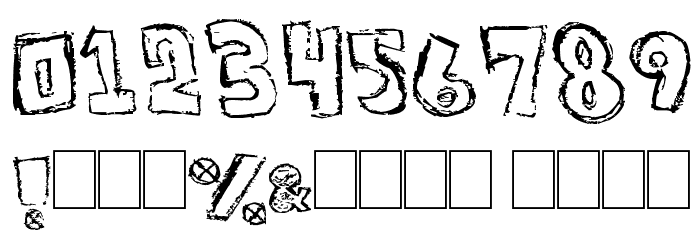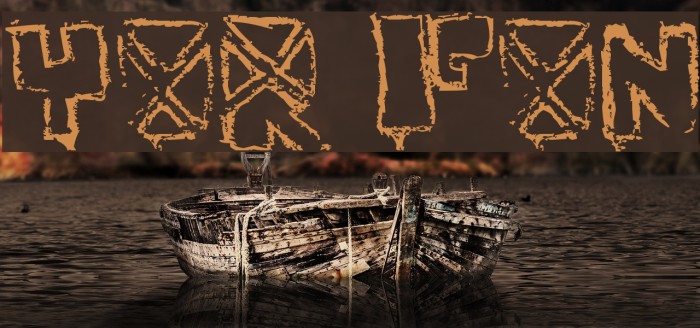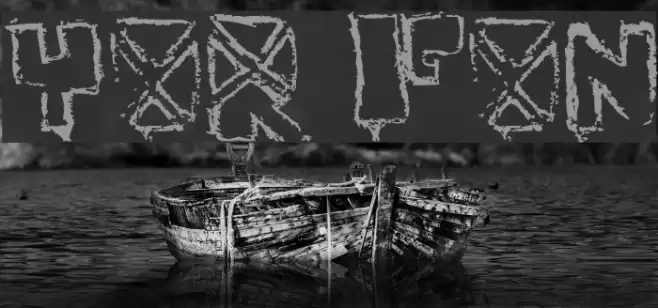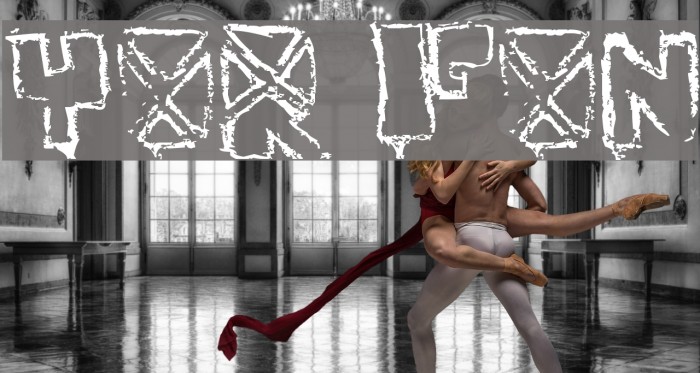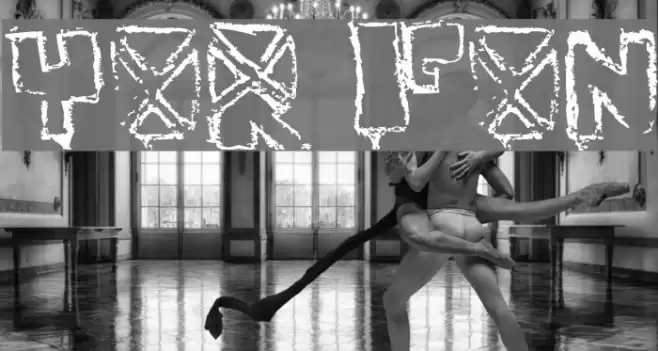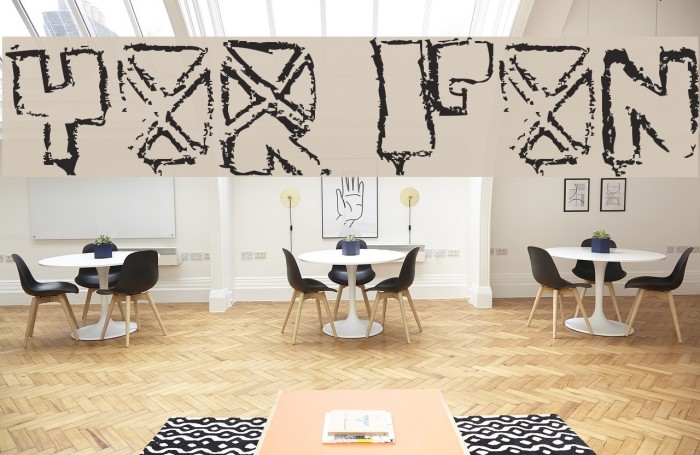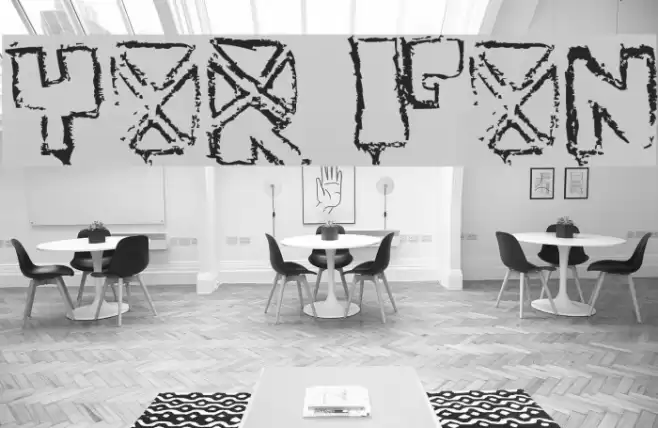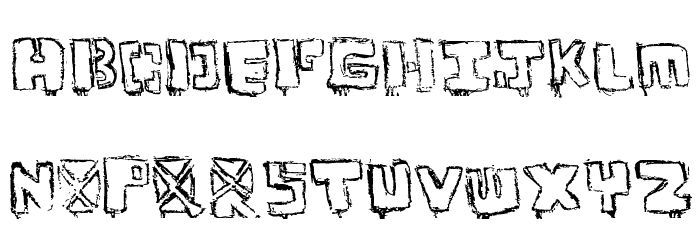
Your Font Font
✎ Distorted Eroded
Этот шрифт содержит 70 символов. Нажмите на любой символ для подробностей.
| Категория | Distorted Eroded |
| Общий стиль | Grunge, Edgy, Hand-drawn |
| Рекомендуемые проекты | Ideal for album covers, posters, streetwear branding, or any design needing a bold, edgy look. |